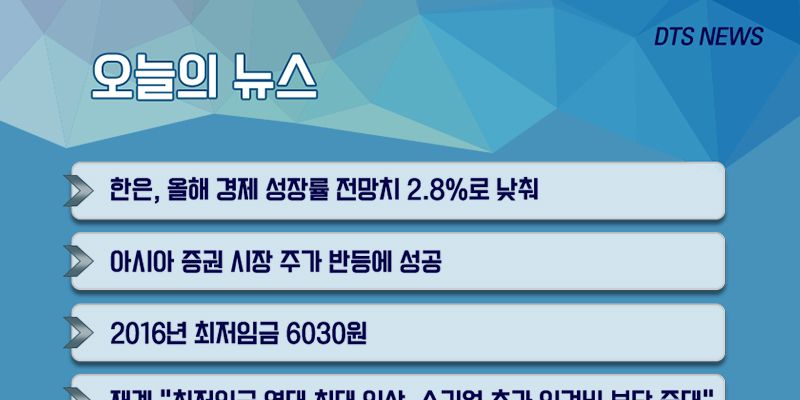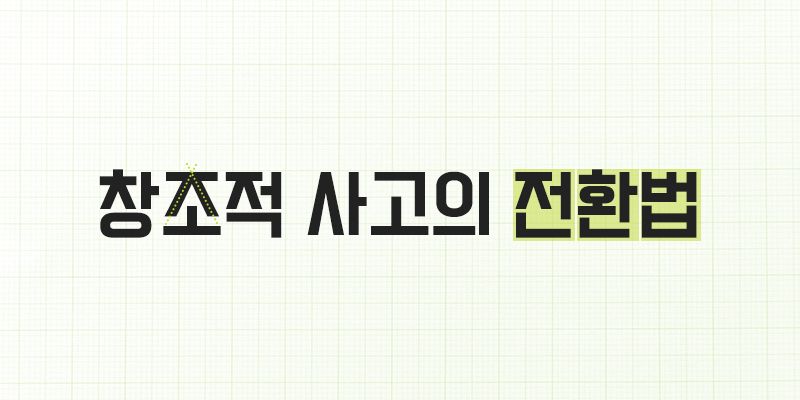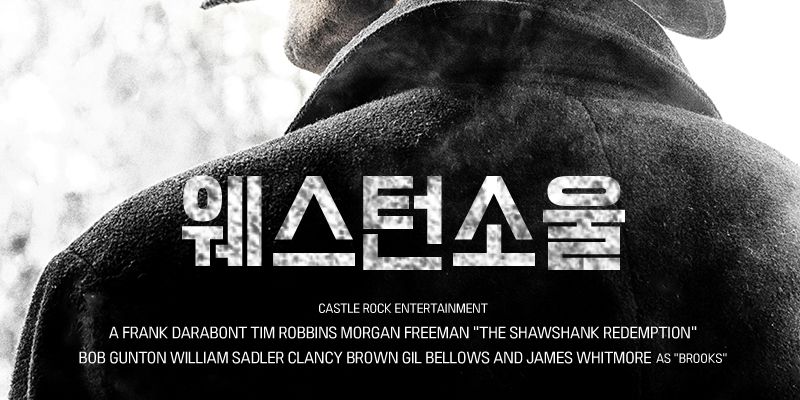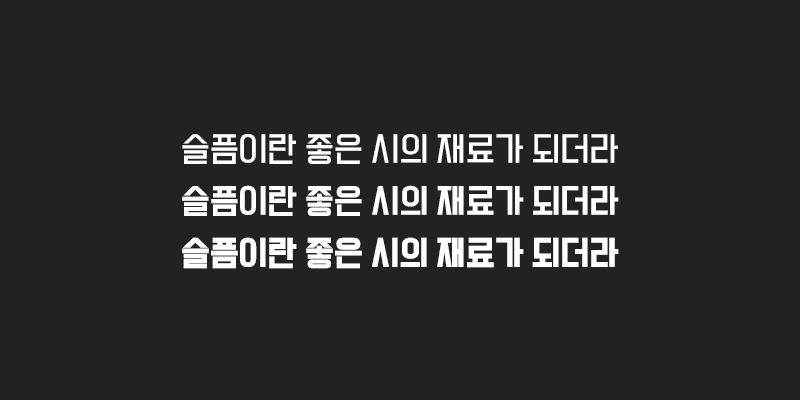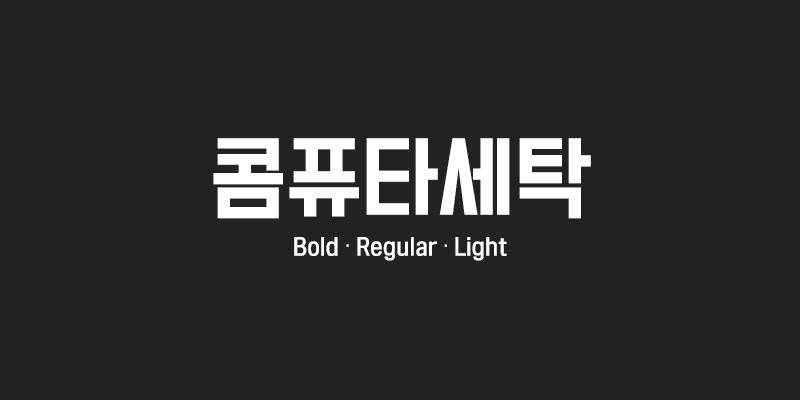
210 Computersetak è progettato sulla base dei design Hangul sui vecchi segnali stradali in Corea. Per enfatizzare un’atmosfera retrò, il design utilizza tratti dritti anziché curvi per emulare lo stile delle lettere ritagliate a mano usando un coltello. Queste forme salde e semplificate delle lettere emanano una sensazione analogica.